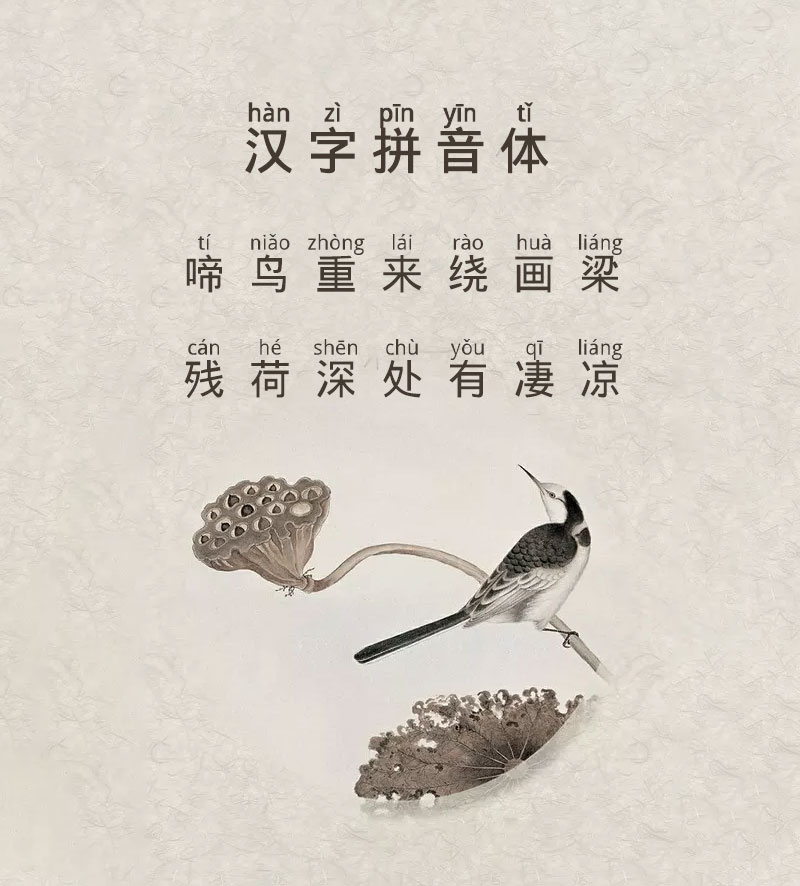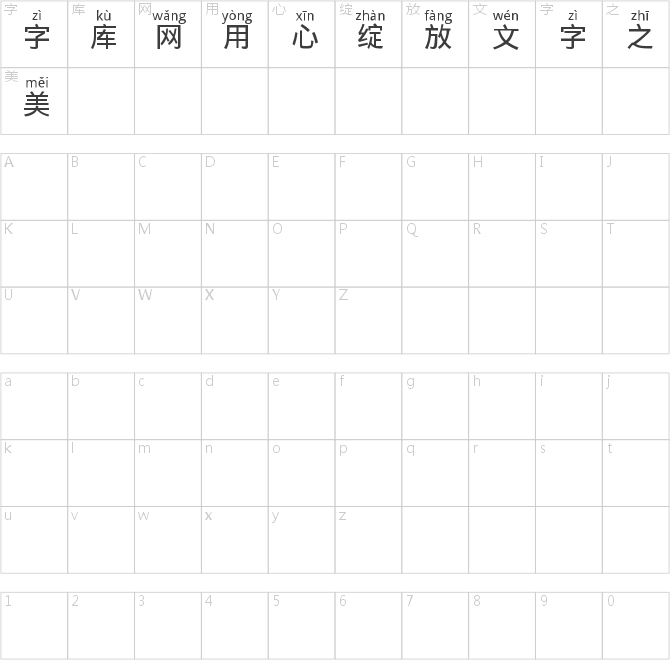
漢字拼音體 詳情頁
字體名稱: 漢字拼音體
漢字拼音體
漢字拼音體一款比較特別的字體, 字體的文字頭上自帶拼音。 用來幫助學生更快地學習和閱讀漢語的字體,特別是對教育類的設計比較有用。軟件顯示字體名稱 Hanzi-Pinyin-Font Regular,字體不支持數字和標點符號,簡體繁體漢子都支持的不錯。